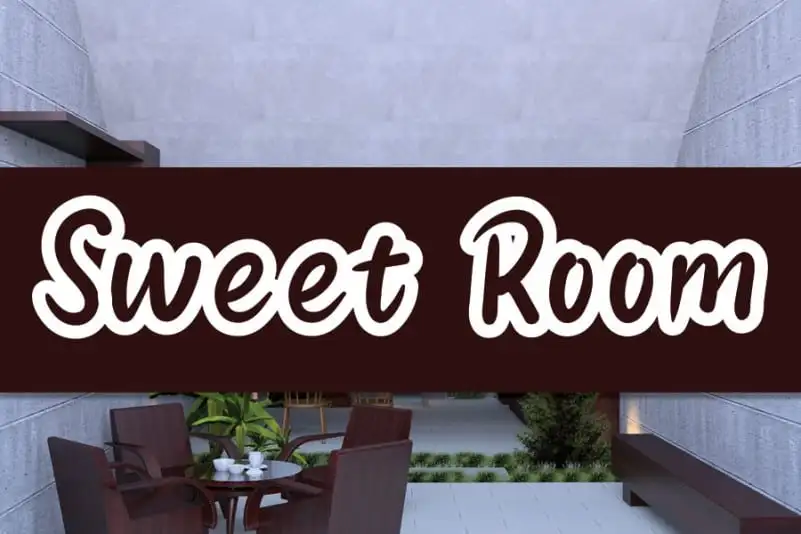
A Sweet Room Script Font é uma elegante fonte à mão livre que transmite sofisticação com seu estilo tipográfico clássico enquanto mantém uma atmosfera atual e fresca. Esta fonte foi meticulosamente criada pelo designer andikastudio para se tornar um verdadeiro favorito. Perfeita para os projetos que precisam de um toque de elegância, a Sweet Room Script Font é ideal para aqueles buscando trazer uma paleta única e vibrante a seus trabalhos. Seja você criador de arte digital ou designer gráfico, esta fonte será uma escolha perfeita para criar texturas únicas e emotivas que se destacarão em qualquer projeto. Com sua influência clássica, mas sem perder o frescor contemporâneo, a Sweet Room Script Font oferece um design único e autêntico. Esta fonte é mais do que simplesmente uma maneira de escrever – ela é um recurso visual para trazer suas ideias ao vivo em qualquer projeto, seja ele digital ou impresso. Adorei esta fonte porque ela não apenas proporciona um visual agradável, mas também permite explorar diferentes estilos e tamanhos de letra, garantindo que você possa moldá-la para sua necessidade específica. Tornando-se uma escolha clara para quem busca a perfeição em cada caractere – o Sweet Room Script Font é uma verdadeira fonte da preferência.